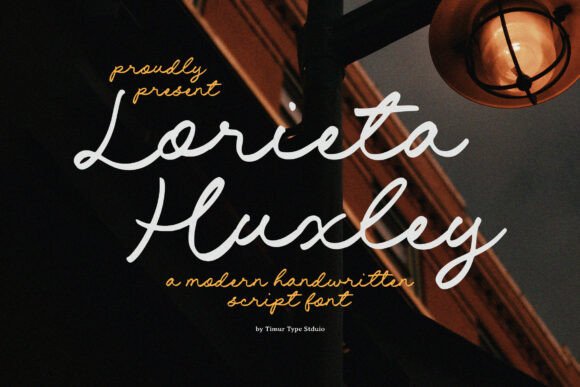
Lorieta Huxley
Jika anda sedang mencari aset berkualiti tinggi seperti Lorieta Huxley, pakej premium ini merupakan pilihan yang hebat untuk projek kreatif anda.
Dicipta dengan ketepatan, Lorieta Huxley menyediakan vektor yang bersih, tipografi yang licin dan lesen komersial untuk ketenangan fikiran.
Sama ada anda mencipta produk POD (Print on Demand), jemputan perkahwinan atau grafik media sosial, Lorieta Huxley amat bersesuaian.